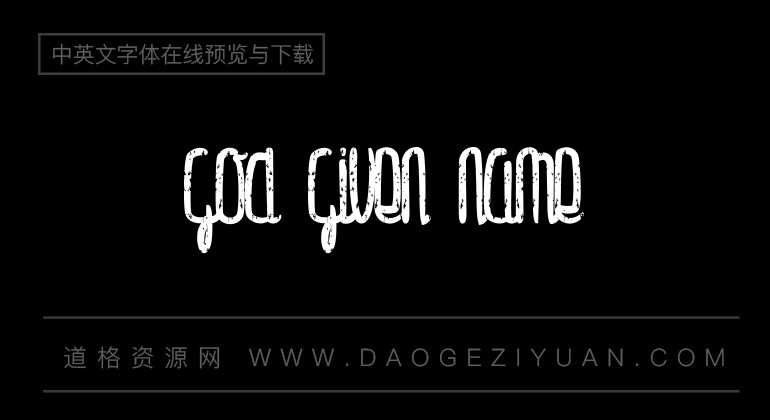
God Given Name
God Given Name 是一款由字体设计师 Alex Kaczun 创作的手写字体。它采用原生的笔迹,拥有细腻的线条和温暖的感觉,可以为任何设计提供灵动的视觉效果。它的设计灵感来源于每个人都有一个神赐的名字,而这款字体正是为了表达这一概念。God Given Name 具有良好的可读性,可以用于制作各种海报、招牌、商标等设计,是一款非常适合用于个性化设计的字体。
God Given Name是一款非常不错的手写艺术字体,具有很好的视觉感,适合于文化类的宣传设计、商业类品牌的广告和产品包装设计以及个性化文字排版等较多场景。